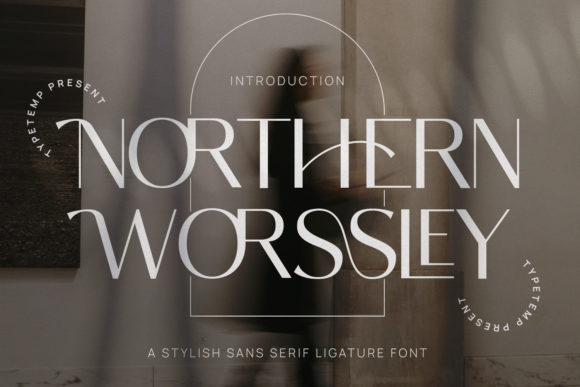
Northern Worssley - это элегантный и тонкий шрифт. Его можно использовать для различных целей, таких как логотипы, свадебные приглашения, заголовки, футболки, бланки, вывески, этикетки, новости, плакаты, значки и многое другое.